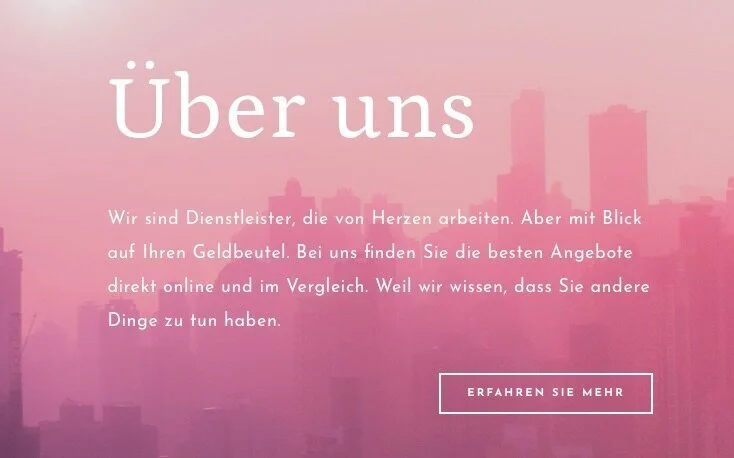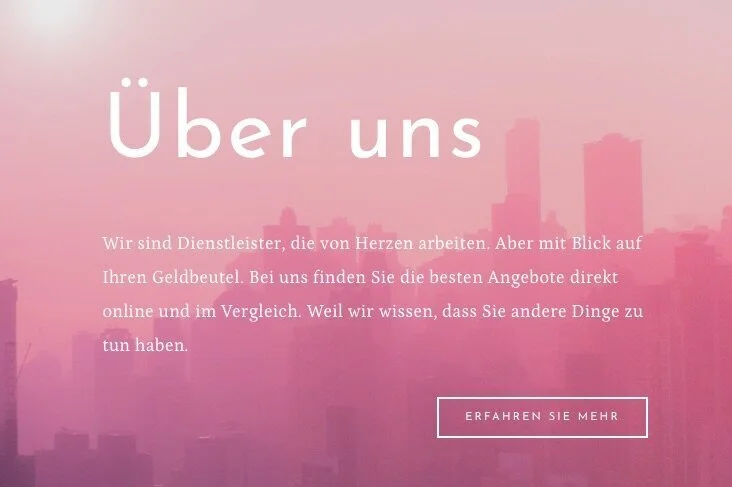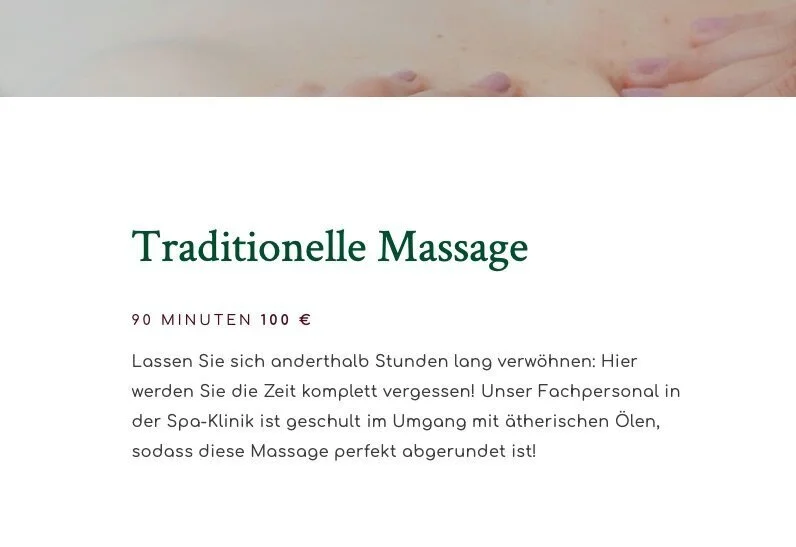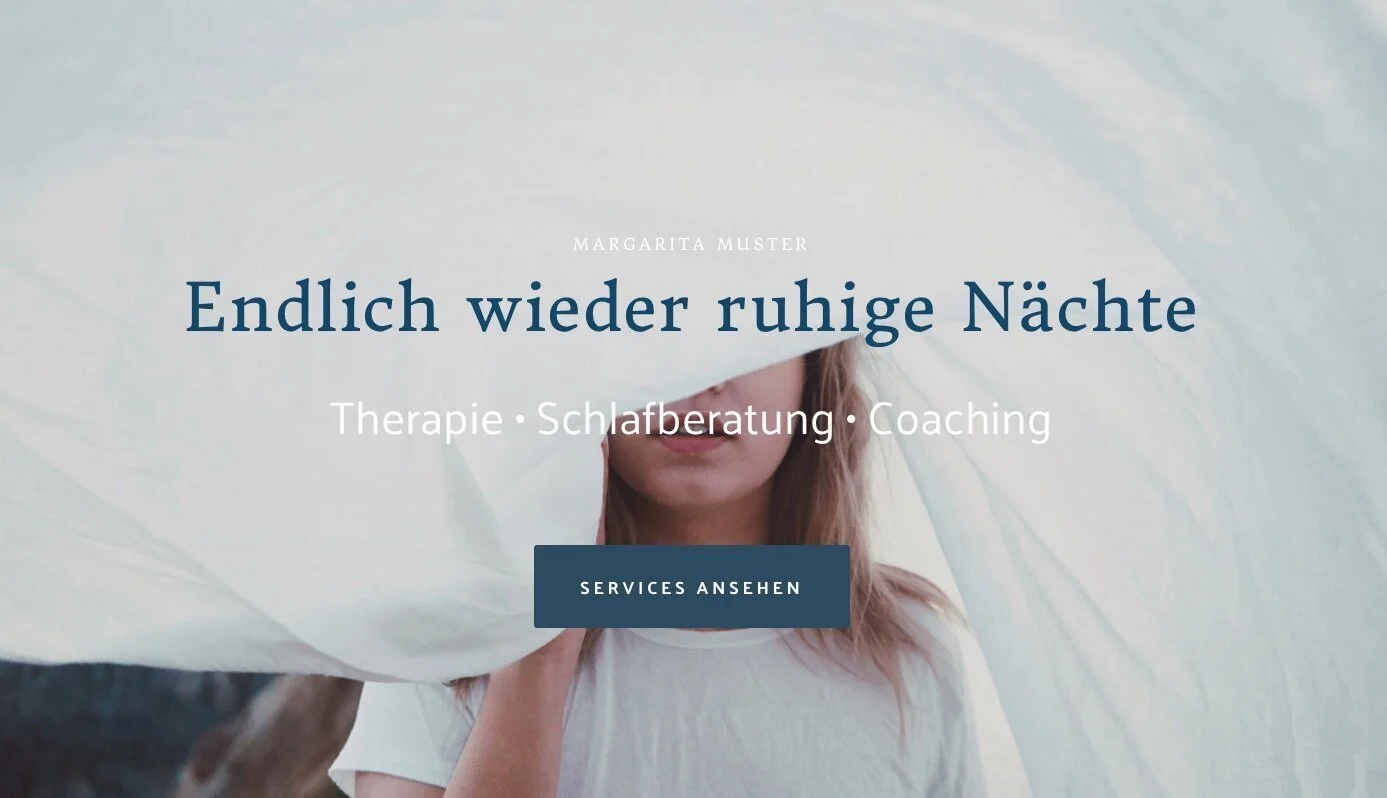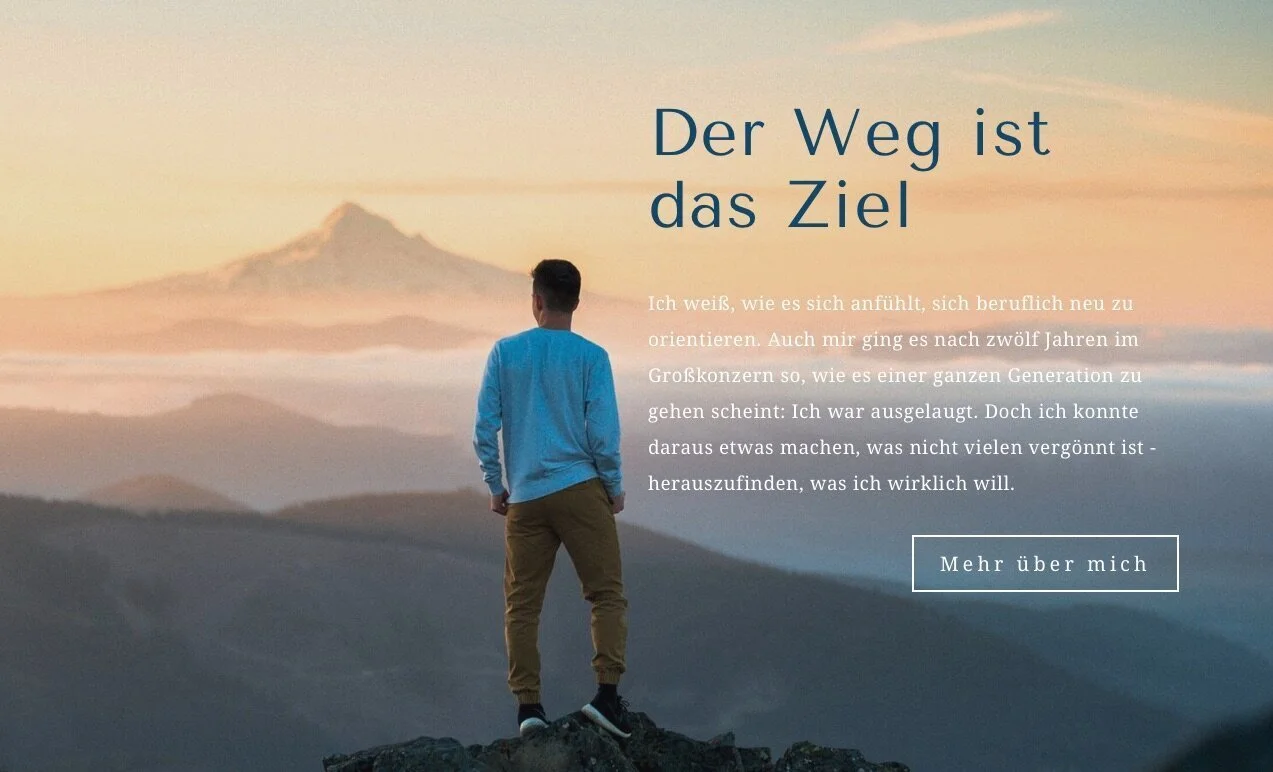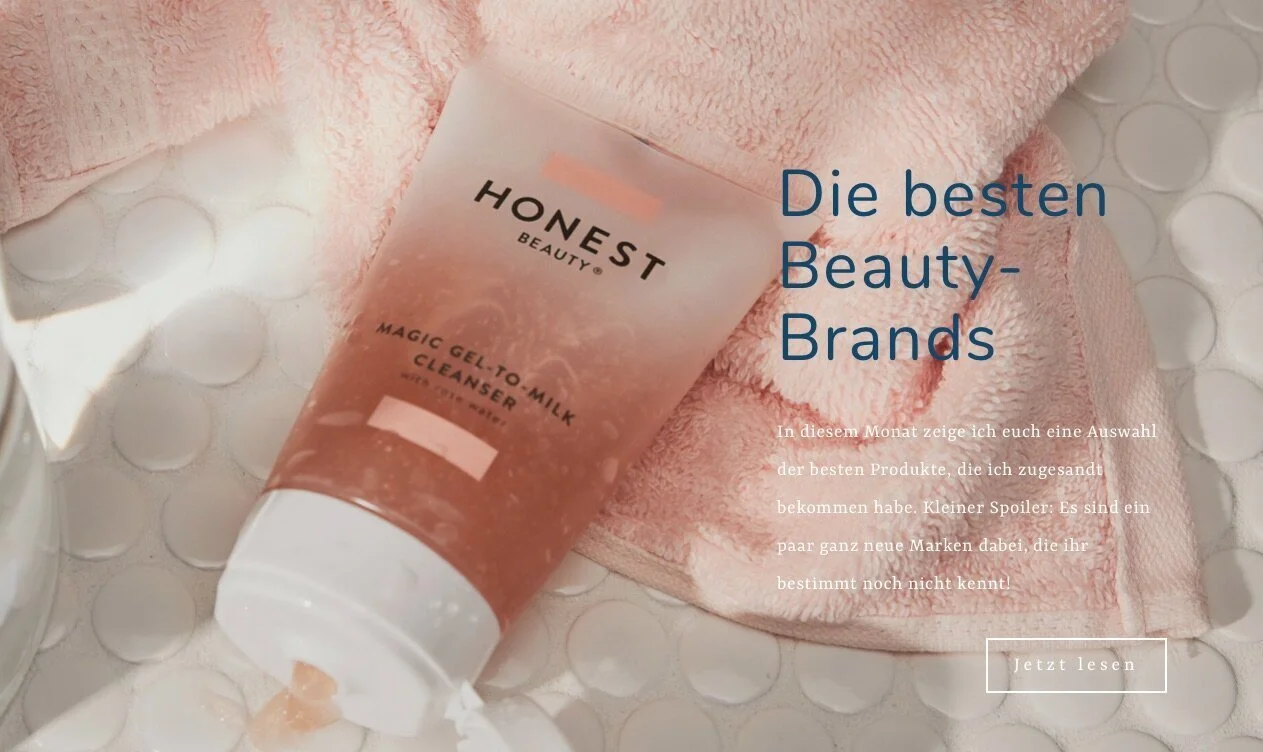
Die beliebtesten Google Fonts wie Roboto, Montserrat oder Open Sans werden mittlerweile auf einer Vielzahl an Websites verwendet.
Aber was ist mit den Geheimtipps? Den Schriftarten, die nicht jeder kennt - die aber deine Seite absolut gut aussehen lassen?
In unserer Übersicht findest du einige tolle Google Fonts Kombinationen, mit denen deine Website gleich deutlich mehr nach “Design” aussieht. Und die gleichzeitig auch in verschiedenen Größen gut lesbar sind.
Google Font Kombinationen, die nicht alle haben
Josefin Sans und Petrona
Diese Kombination ist perfekt, wenn du eine Website gestaltest, die modern, aber trotzdem luftig-leicht und frisch aussehen soll. Die Kombination der jugendlich und elegant wirkenden Google Font Josefin Sans mit der Serifenschrift Petrona bringt eine schöne Dynamik in das Design.
Hier wird Petrona als Überschrift verwendet und Josefin Sans im Fließtext und für den Button.
Umgekehrt sieht das so aus: Wenn Josefin Sans als Überschrift gewählt wird, bekommt die Seite gleich einen ganz anderen Look.
Comfortaa und Crimson Text
Diese Kombination funktioniert so gut, weil die serifenlose Schrift Comfortaa sehr modern ist, die Kombination mit der eher traditionellen Crimson Text aber eine schöne Balance herein bringt.
Hier siehst du, wie die Überschrift (in Grün) den sehr modernen Text etwas “beruhigt”.
Übrigens: Crimson Text sieht auch sehr gut zur Google Font Open Sans aus - die aber auch zu den meist genutzten Google Fonts gehört.
Donegal One und Palanquin
Dies sind zwei Schriften, von denen die wenigsten schon einmal gehört haben. Beide sind aber wunderschöne, moderne Schriften, die in Kombination sehr stimmig aussehen.
Hier im Beispiel oben habe ich die Serifen-Schrift Donegal One (“Endlich wieder ruhige Nächte” in Blau) zusammen mit der modernen Google Font Palanquin verwendet.
Palanquin ist speziell für den digitalen Gebrauch designt und ist zusammen mit Donegal One, was wiederum gut lesbar ist, auch in umgekehrter Kombination super zu kombinieren.
Tenor Sans und Noto Serif
Gemäß Google ist die schöne serifenlose Schrift Tenor Sans eigentlich für Fließtext designt, ich persönlich finde sie aber mindestens genau so schön als Überschrift. Auf dem Bild unten siehst du sie in der Überschrift in Kombination mit Noto Serif, eine Serifenschrift, die etwas Spielerisches hat.
Weil die Überschrift so minimalistisch ist, passt es hier sehr gut, dass der Fließtext einen anderen Stil hat. Zwei Serifenschriften würde ich mit Noto Serif allerdings eher nicht kombinieren.
Nunito und Rasa
Ebenfalls eine schöne Serifen-trifft-Serifenlos-Kombination sind die hier in Blau verwendete Nunito und dazu passend im Fließtext die eher wenig bekannte Schriftart Rasa.
Von Nunito (die oben im Bild als Überschrift verwendet wird) gibt es übrigens noch die abgewandelte Schriftart Nunito Sans, die ebenfalls bei Google Fonts verfügbar ist. Vom Look her ist diese Variante dann noch etwas “eckiger”.